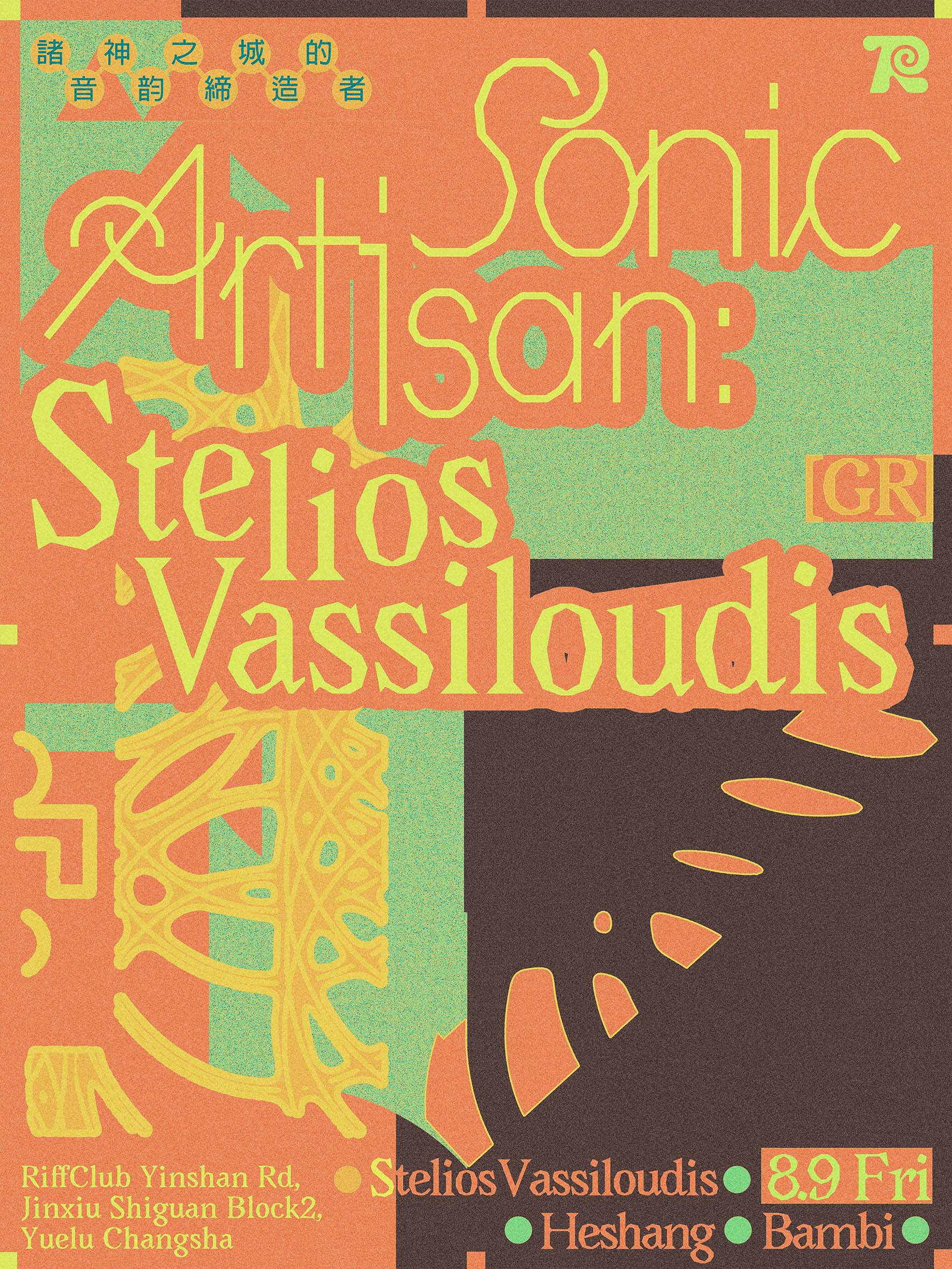
Avara
Raphaël, Wei, Lucas, Walid & Jérémy
Avara est une famille de caractères libre à empattements droits à congés sans aucune courbes. L'emplacement de ses points est exclusivement basé sur une grille carrée. Le choix derrière ce parti pris créatif visait à faciliter la collaboration sur la police, qui se traduit par des formes radicales et très contraintes. Elle a été initiée et publiée pour la première fois en novembre 2011 par Raphaël Bastide; elle a été mise à jour depuis lors et finalement publiée ici. Elle pourrait être mise à jour à nouveau à l'avenir, peut-être par vous.
Le style Gras a été initié par Raphaël Bastide et poursuivi par Wei Huang et Lucas Le Bihan; le style Gras Italique par Lucas Le Bihan; le style Noir a été initié par Walid Bouchouchi et Jérémy Landes, puis il a été épaissi à nouveau et terminé par Lucas Le Bihan.